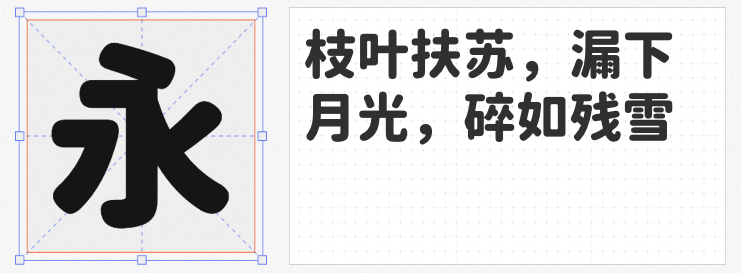
在信息爆炸的视觉战场,一款独具创意的字体能瞬间抓住受众目光。以下四款免费商用字体,以传统文化为魂、现代设计为骨,为海报与宣传设计注入鲜活生命力,让创意表达突破次元壁。
1. 一品启航体
这款以书法为基底的字体,将传统笔墨的遒劲转化为昂扬向上的视觉语言。笔画转折处如扬帆起航的桅杆,横竖撇捺间暗藏破浪之势。其开放商用的属性,让公益海报、品牌宣言等场景得以自由承载进取精神,每个字符都成为传递正能量的视觉符号。
2. 浪课江湖联盟简体
当书法遇见刀刻艺术,这款字体以剑锋般的笔触劈开设计常规。笔画边缘的硬朗切割感,既保留传统书法的飞白韵味,又融入金属质感的现代锋芒。特别适合武侠主题、运动品牌等需要彰显力量感的设计场景,让海报瞬间充满江湖豪情。
3. 江城圆体 700W
基于经典圆体改良的这款字体,通过简体化改造完美适配大陆设计语境。圆润的笔画如春风拂面,在保持高辨识度的同时,消除了繁体字带来的阅读隔阂。无论是儿童教育海报还是生活类宣传物料,其柔和的视觉特质都能营造亲切感,成为连接两岸审美的文化纽带。
4. 仓耳舒圆体 W05
取法苏轼词中“缺月舒窈窕”的意境,这款字体以粗细渐变的笔画勾勒出月色般的柔美轮廓。独特的慵懒气质非但没有削弱可读性,反而为茶饮、文创、艺术展览等品牌海报增添了禅意美学。每个字符都像在纸上舒展身姿,让设计自然流淌出轻松愉悦的视觉韵律。
从书法的气韵生动到几何的理性构建,这四款免费字体以开放姿态赋能创意产业。它们不仅是设计工具,更是文化传承的载体与情感共鸣的触点,助力每个设计者扬帆起航,在视觉江湖中书写属于自己的传奇篇章。